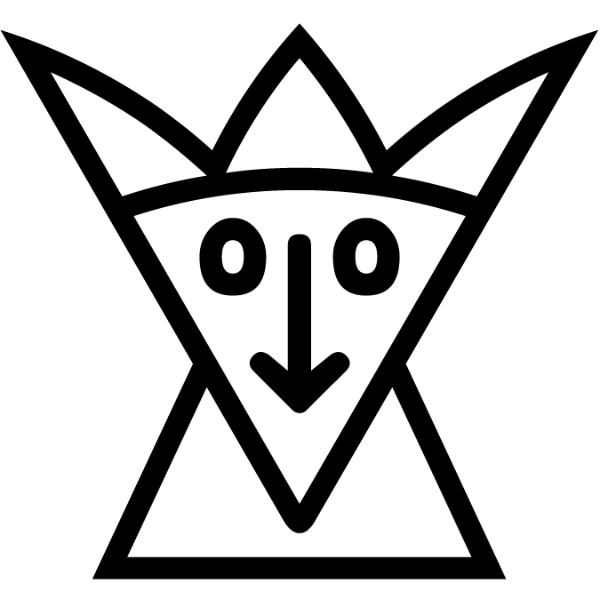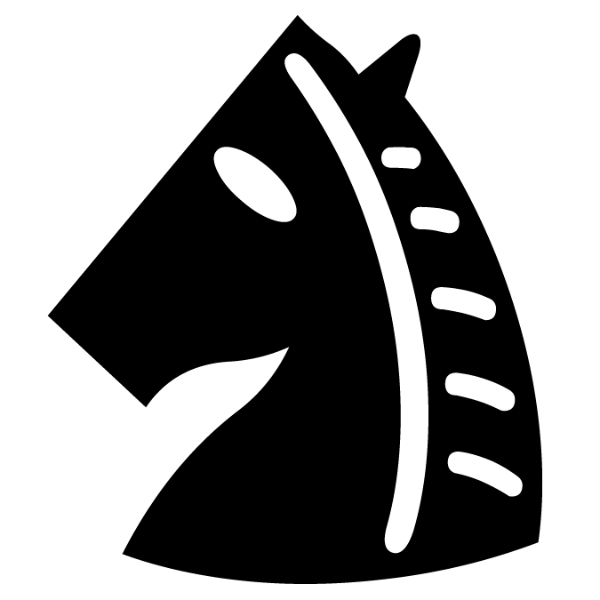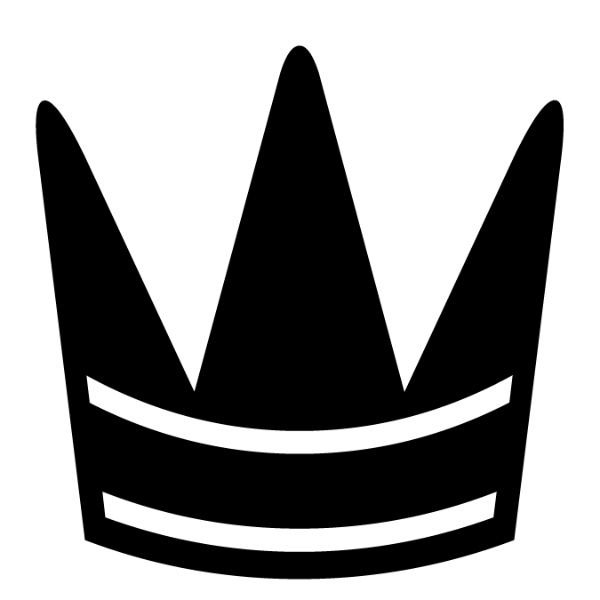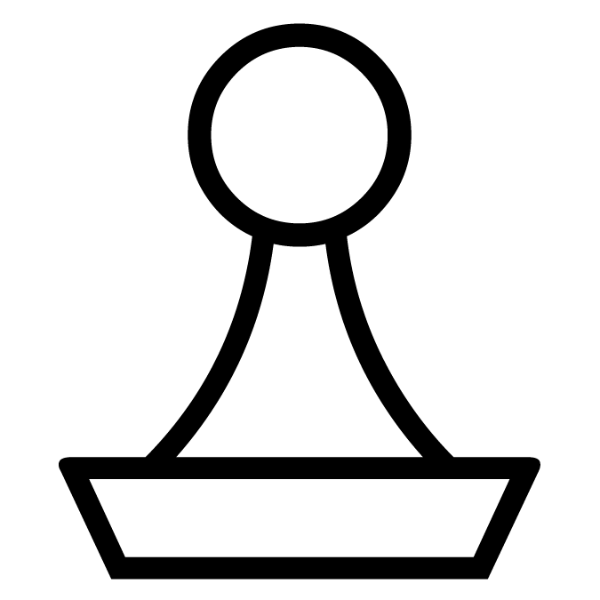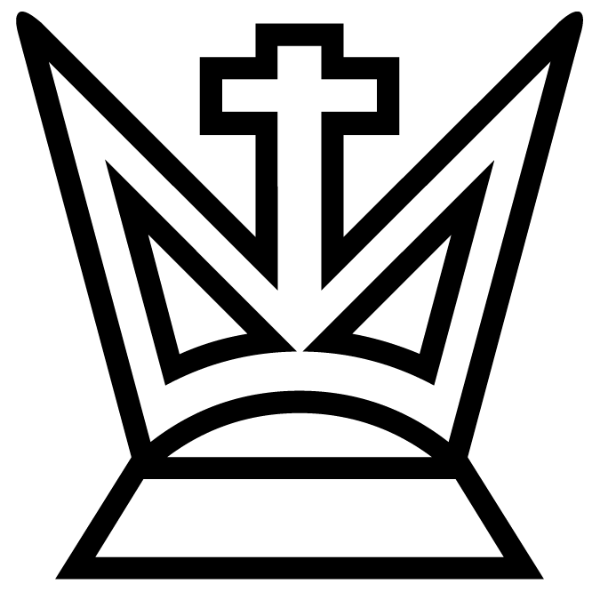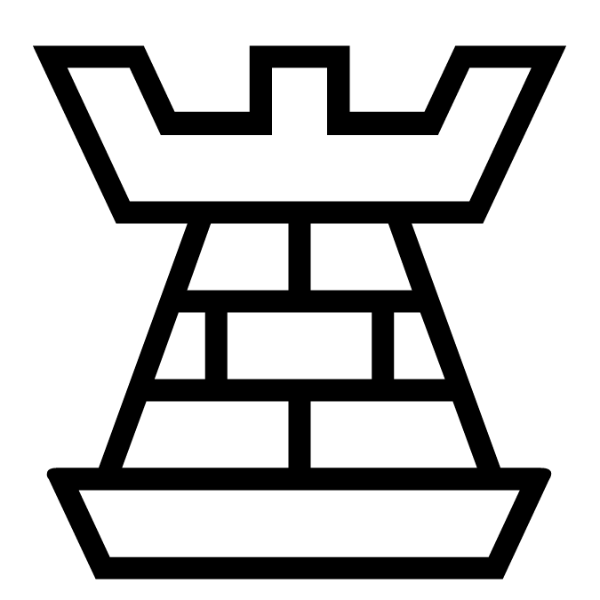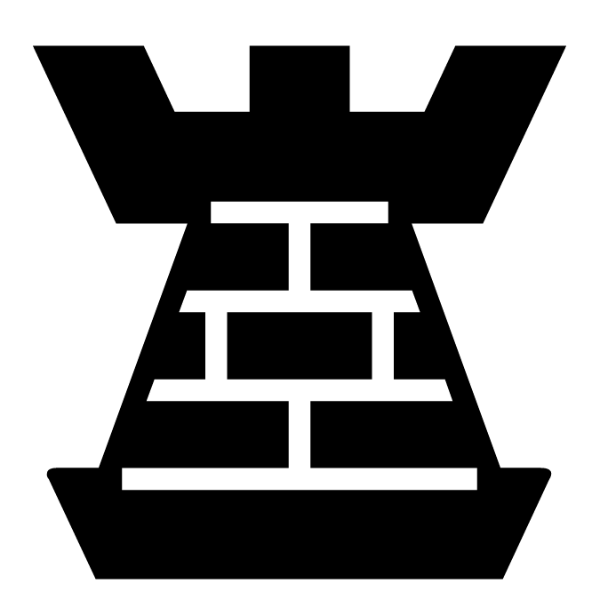
La Fuente Chess Harlequin se distingue por sus formas geométricas, con piezas que combinan triángulos y líneas estilizadas, creando un diseño sobrio y moderno. El alfil, con su forma particular, resalta como una de las piezas más originales de esta fuente.
Juego de Ajedrez con la Fuente Harlequin: